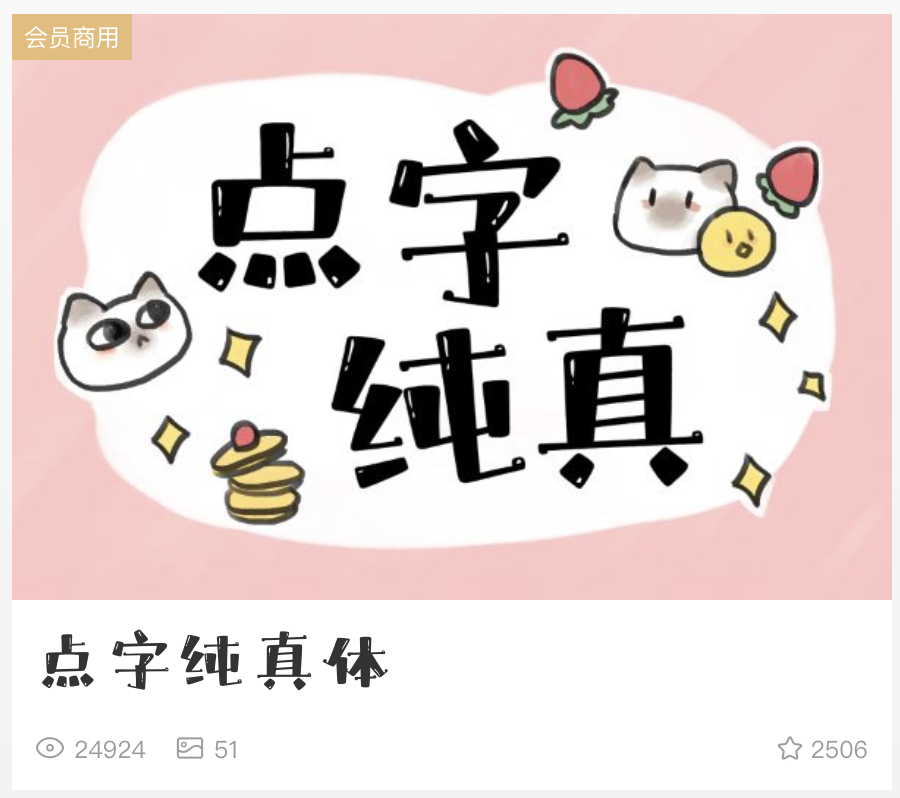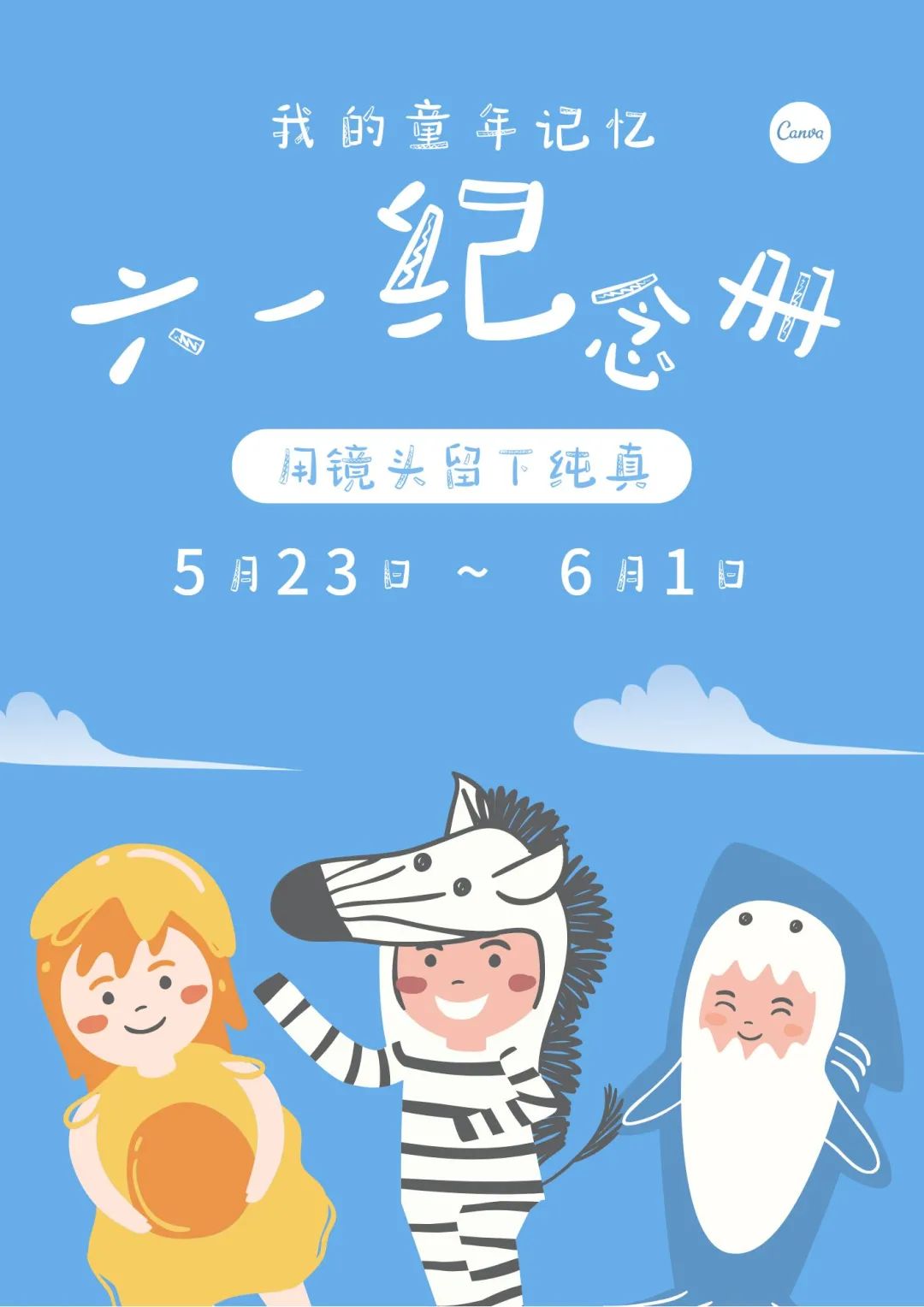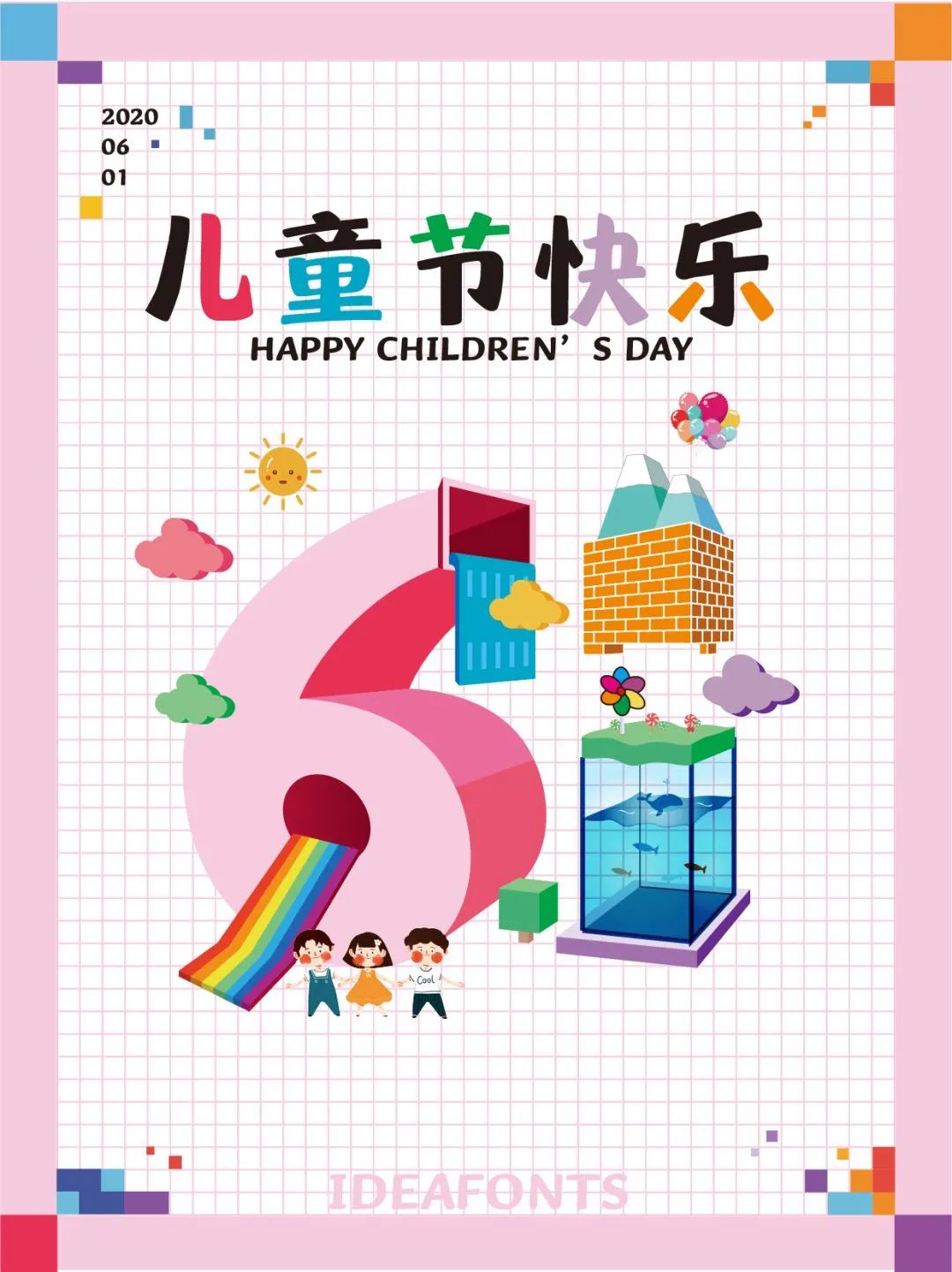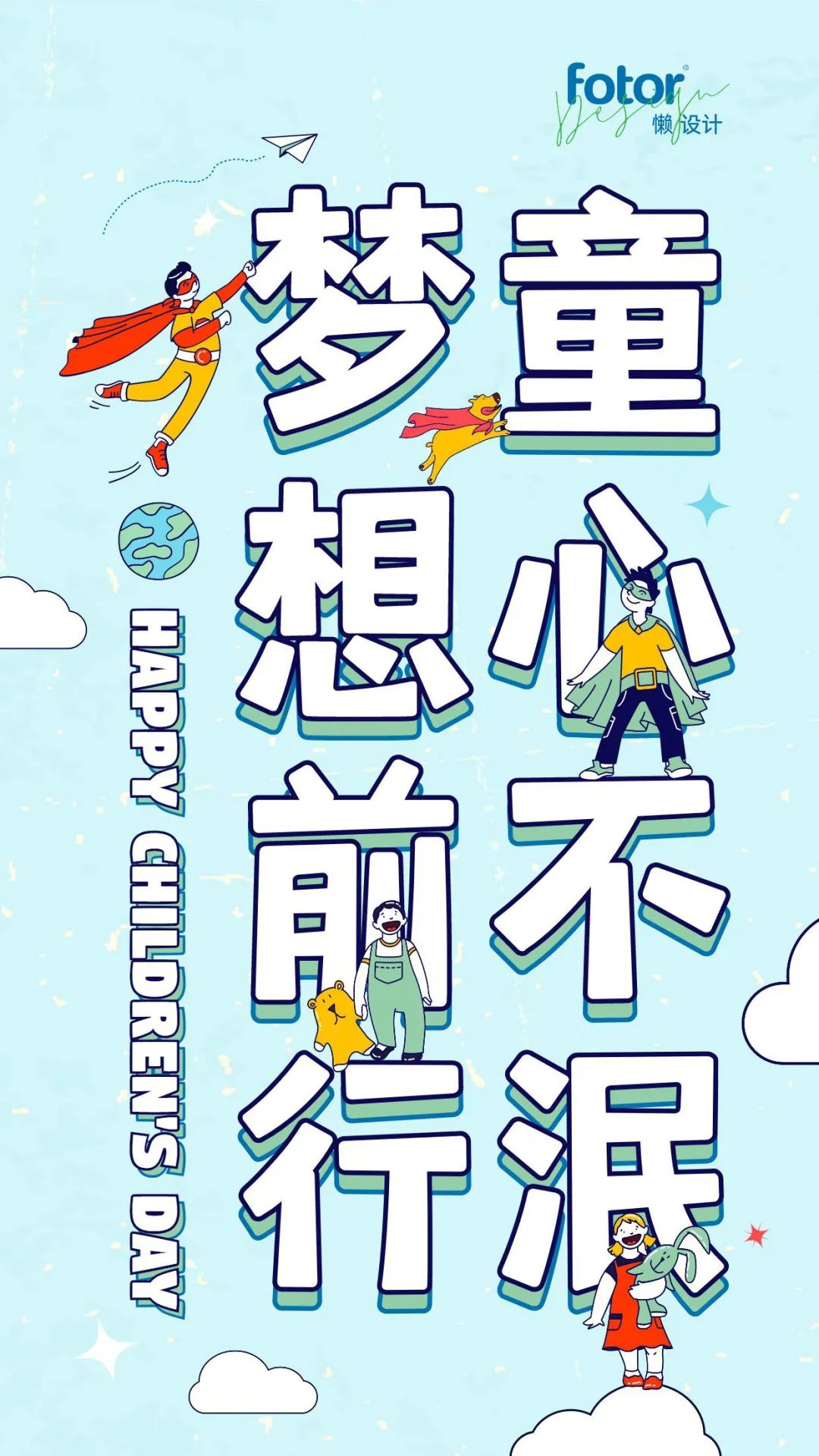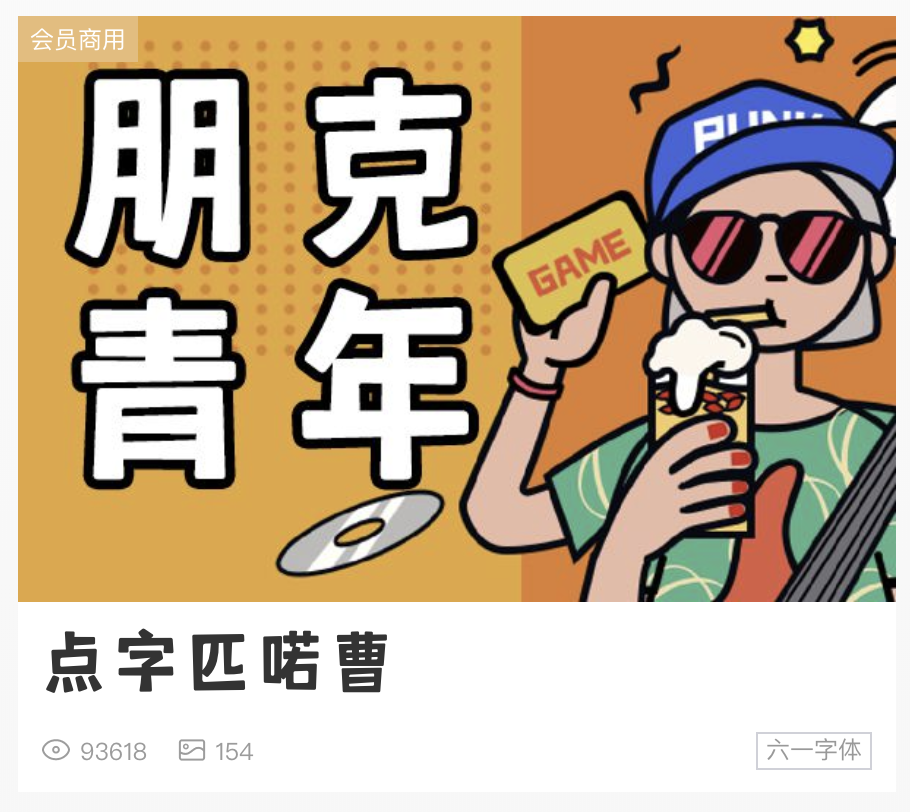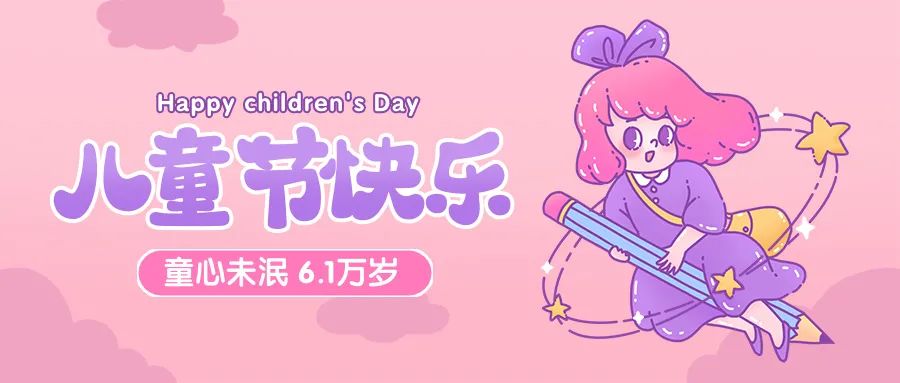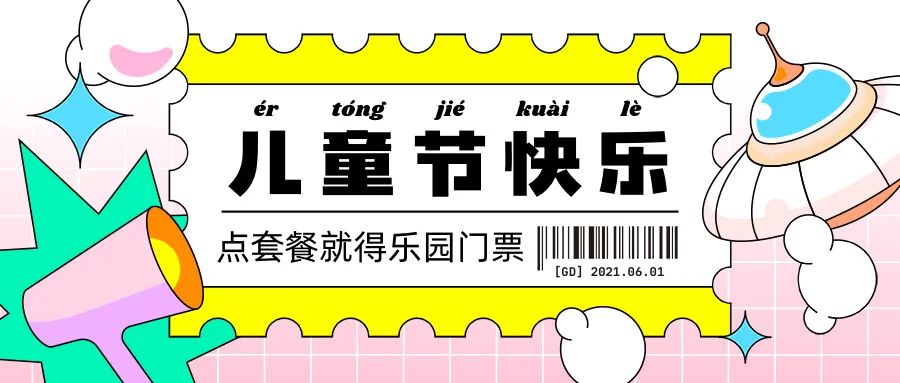
如果你不知道怎么展现儿童的快乐,柚子告诉你一个绝!对!不!会!出!错!的秘诀,那就是可爱风字体。
🌈点字纯真体✨
🌈点字童稚体✨
🌈点字奇妙体✨
🌈点字匹喏曹✨
🌈点字QQ糖✨
可爱风的字体太多啦,根本用不过来。那如果另辟蹊径,用一些非常流行的大色块,怎么配字呢?
🌈点字墩墩体✨
🌈点字综艺体✨
🌈字体管家手写海报体✨